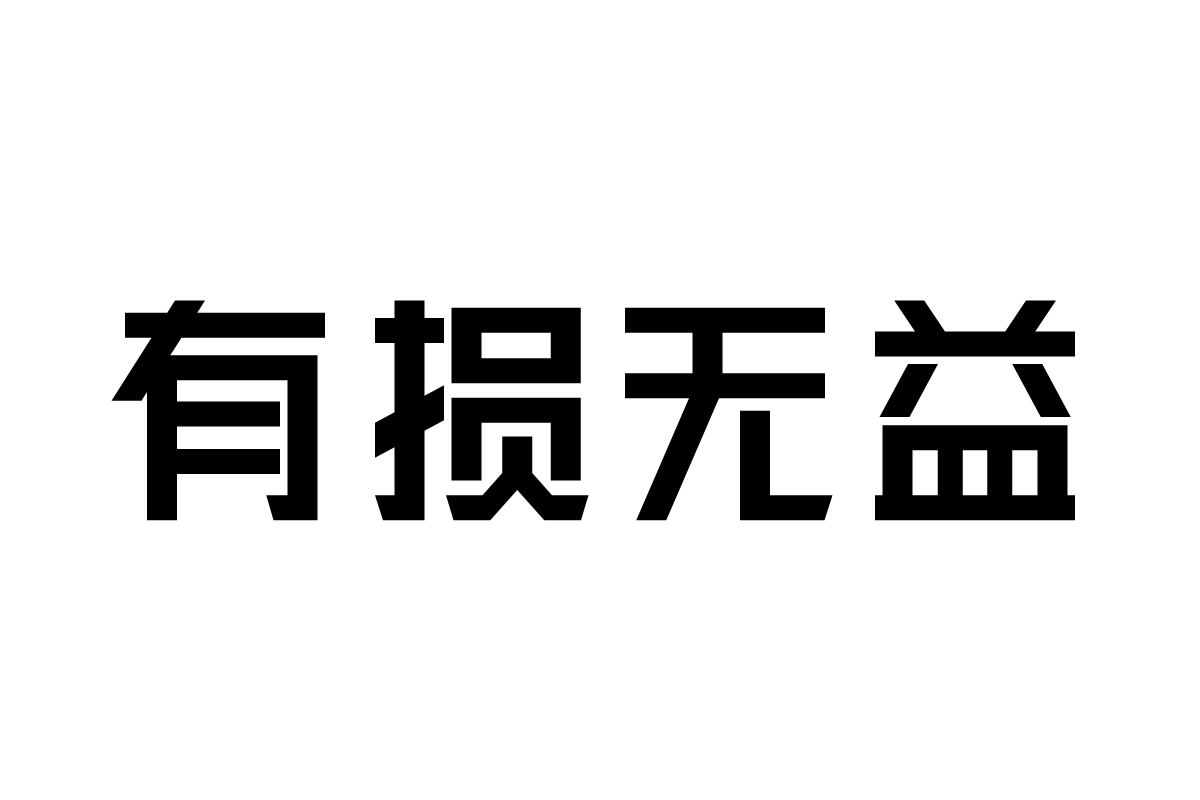
三极锐黑(Sansui Rui Black)是一套由日本字体设计师森田康博(Kanno Takaaki)设计的无衬线字体。这款字体以其简洁、现代的设计而受到广泛欢迎,广泛应用于各种品牌标识、广告、网页设计等领域。
三极锐黑的特点如下:
1. 无衬线设计:三极锐黑采用无衬线风格,线条清晰、简洁,易于阅读和识别。这种设计使得字体在各种应用场景中都能展现出良好的视觉效果。
2. 可扩展性:三极锐黑支持多种字重,包括常规、粗体、斜体等,满足不同字体大小和风格的需要。这使得设计师可以根据自己的需求选择合适的字重,实现个性化的字体设计。
3. 易用性:三极锐黑的字符间距和行间距设置灵活,方便设计师调整字体的美观度。同时,该字体还提供了丰富的字符集,包括常用拉丁字母、数字、标点符号等,满足各种文字处理需求。
总之,三极锐黑是一款功能强大、适用范围广泛的无衬线字体,深受设计师和用户的喜爱。